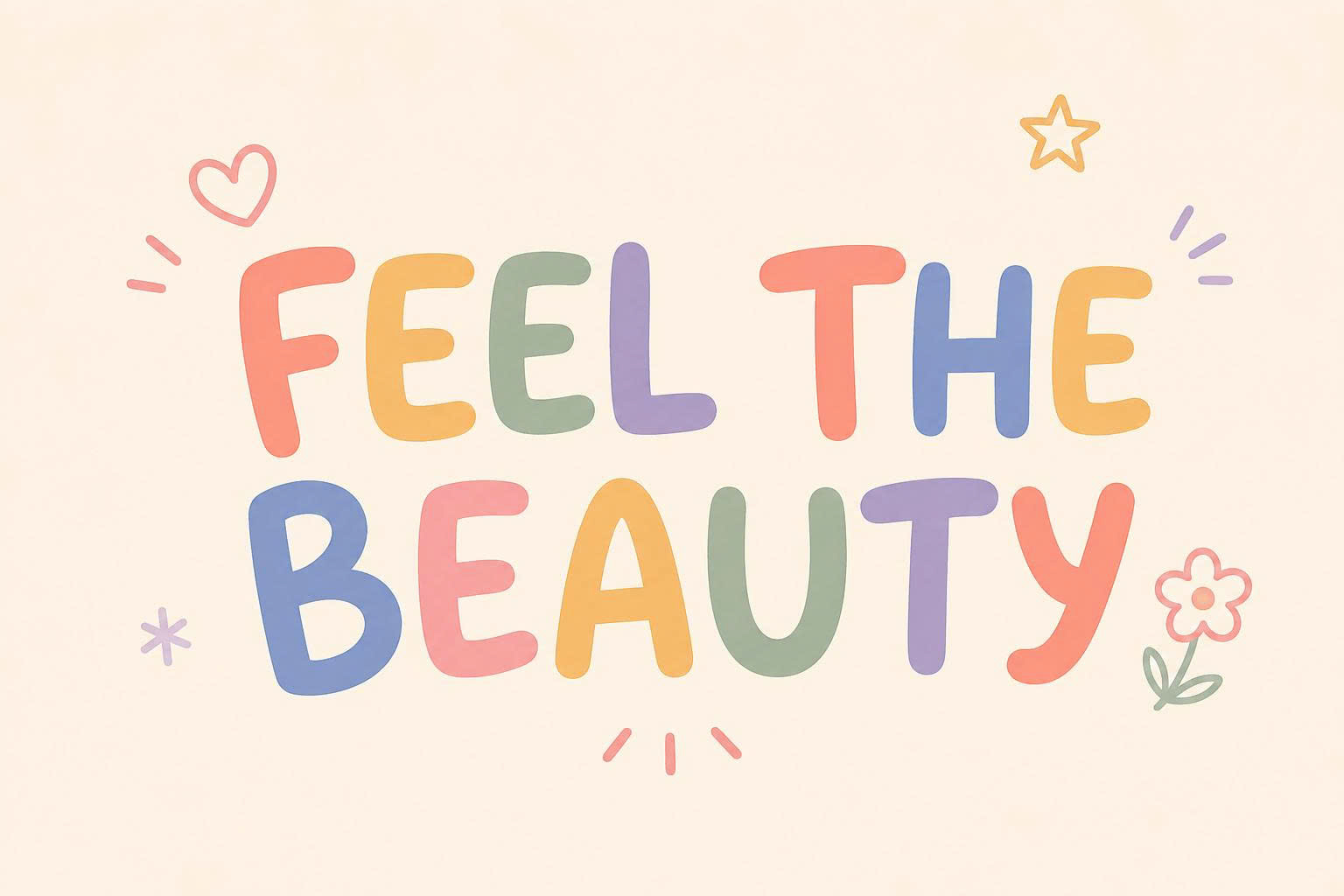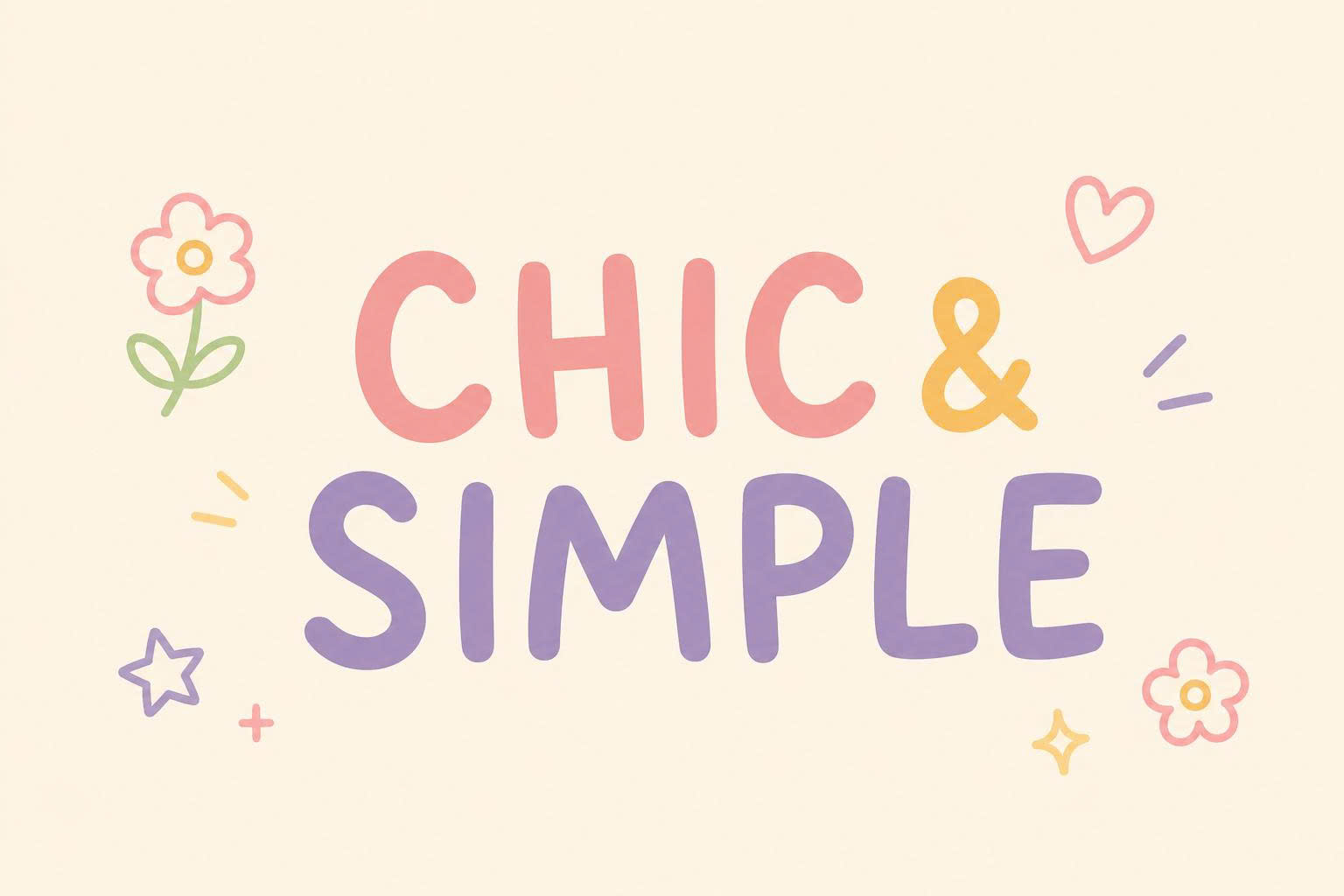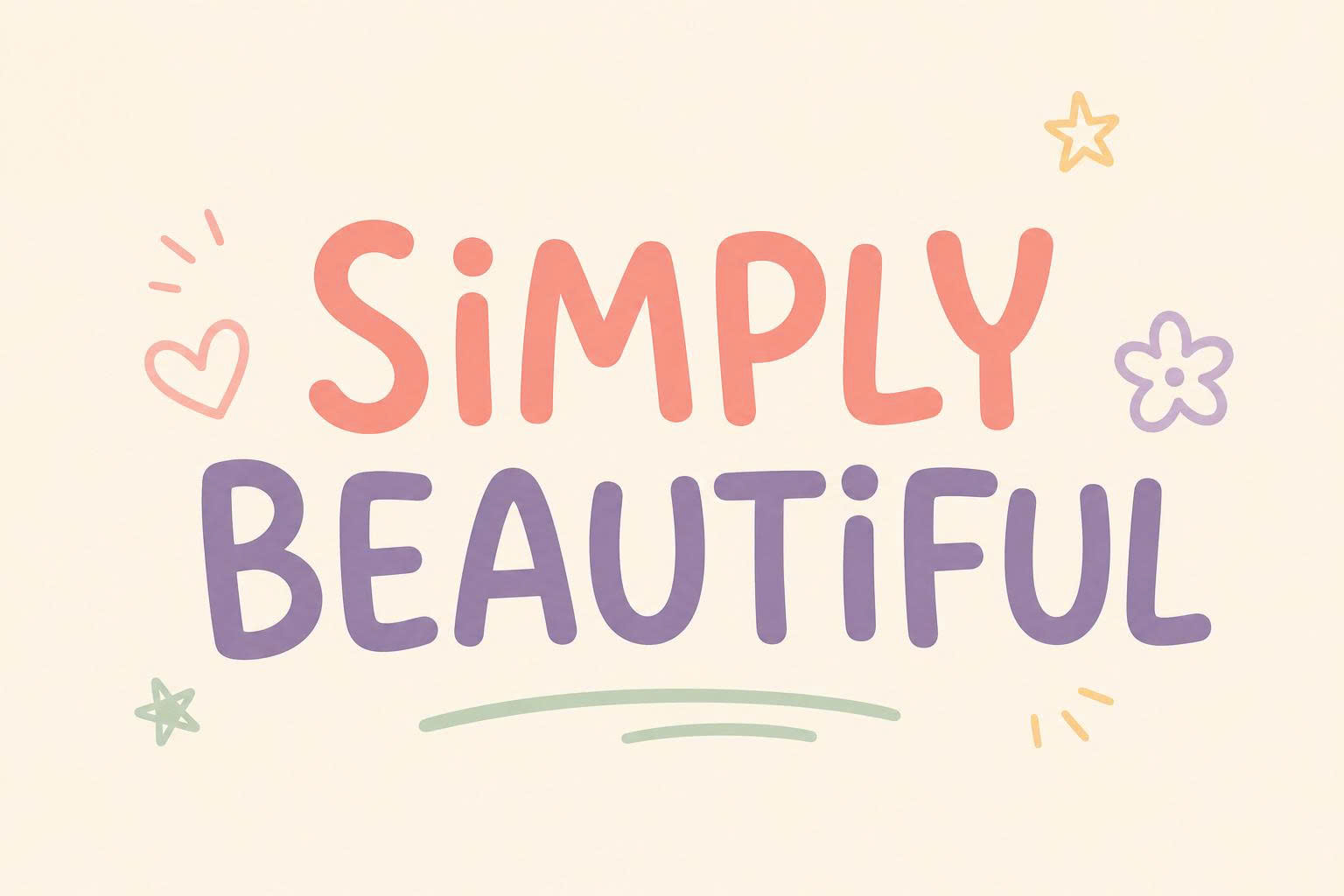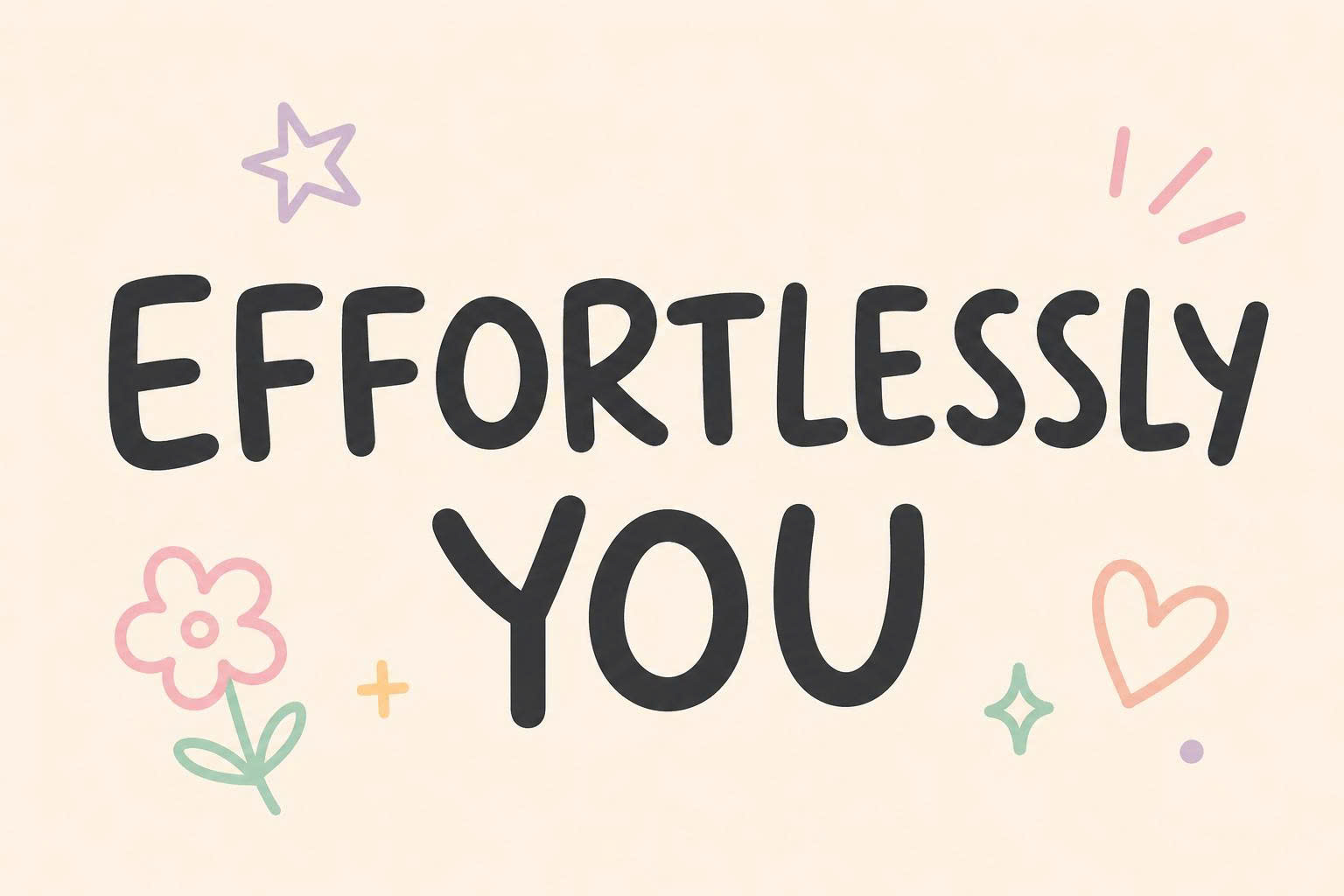
One Little font Việt hóa là bộ phông chữ viết tay (Handwritten) mang phong cách vô cùng đáng yêu, hồn nhiên và vui tươi. Với những đường nét mảnh dẻ, hơi nghuệch ngoạc một cách cố ý, One Little gợi nhắc đến nét chữ của trẻ thơ hoặc những dòng nhật ký đầy cảm xúc. Đây là lựa chọn tuyệt vời cho các thiết kế dành cho thiếu nhi, tiệm bánh, hoặc các sản phẩm handmade cần sự gần gũi. Doozypack.vn chia sẻ link tải font One Little Việt hóa chuẩn, giúp bạn sở hữu bộ font One Little tiếng Việt hoàn chỉnh, không lỗi dấu thanh để tự do sáng tạo bao bì và ấn phẩm truyền thông.
Đặc điểm thẩm mỹ của font One Little Việt hóa
One Little không chỉ là một kiểu chữ; nó mang lại một không gian cảm xúc nhẹ nhàng và trong sáng cho bất kỳ bản thiết kế nào sử dụng nó.
Phong cách viết tay dễ thương và đầy cá tính
Đặc trưng lớn nhất của font One Little Việt hóa là sự không hoàn hảo một cách nghệ thuật. Các ký tự có kích thước cao thấp khác nhau, nét vẽ mảnh như bút kim tạo nên sự ngẫu hứng và chân thực. Thay vì sự cứng nhắc của các font chữ hệ thống, One Little thổi vào bản thiết kế một làn gió mới, giúp thương hiệu trở nên thân thiện và dễ mến hơn trong mắt khách hàng.
Hỗ trợ tiếng Việt trọn vẹn, không lỗi font
Nhiều designer thường gặp khó khăn khi sử dụng các phông chữ handwriting nước ngoài vì bộ dấu tiếng Việt thường bị nhảy font hoặc sai lệch vị trí. Phiên bản font One Little tiếng Việt tại Doozypack.vn đã được tinh chỉnh kỹ lưỡng, đảm bảo các dấu thanh (sắc, huyền, hỏi, ngã, nặng) hài hòa tuyệt đối với thân chữ, giúp các dòng slogan hay tên sản phẩm của bạn luôn chỉn chu và đạt độ thẩm mỹ cao nhất.
04 Ứng dụng của font One Little trong ngành sản xuất bao bì
Tại Doozypack.vn, sự dễ thương của One Little mang lại hiệu quả đặc biệt trên các ấn phẩm bao bì thực tế:
- Bao bì ngành bánh và đồ ngọt: Rất phù hợp làm tên thương hiệu hoặc tiêu đề trên hộp bánh cupcake, bánh quy hay kẹo thủ công, tạo cảm giác ngọt ngào và handmade.
- Sản phẩm dành cho mẹ và bé: Dùng cho tem nhãn quần áo trẻ em, hộp đựng quà tặng thôi nôi hoặc các nhãn dán bình sữa, mang lại sự nhẹ nhàng và tin cậy.
- Thiệp chúc mừng và nhãn dán (Sticker): One Little là lựa chọn tuyệt vời để in những câu quote ngắn lên sticker trang trí, giúp sản phẩm thêm phần sinh động.
- Túi giấy cho tiệm văn phòng phẩm: In tên shop bằng font One Little trên túi giấy tạo phong cách trẻ trung và rất “art”.